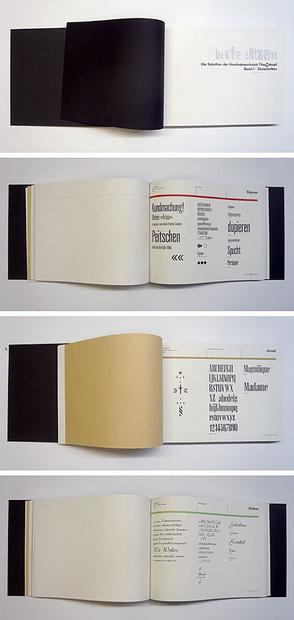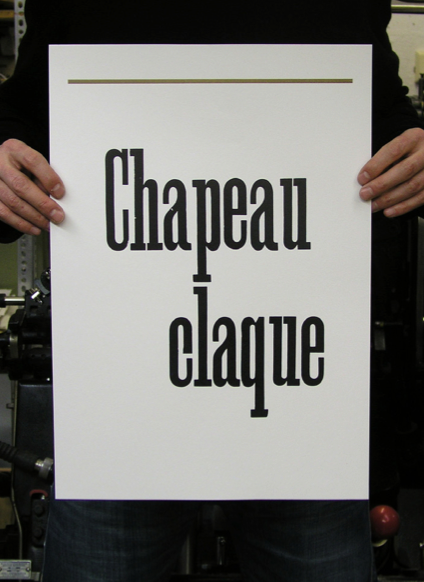
Unter dem Appell »Bitte setzen!« startete die Designschule München in Zusammenarbeit mit der Handsatzwerkstatt Fliegenkopf im Sommer 2008 ein gewagtes Unternehmen: Ein Schriftmusterbuch der rund 170 verschiedenen Schriften der Werkstatt sollte entstehen.
Was zunächst mit den Studierenden begann, wurde bald auf weitere Schriftliebhaber ausgedehnt. Viele entschlossen sich spontan, bei diesem außergewöhnlichen Projekt dabei zu sein und erweiterten den Kreis der Mitarbeiter weit über die Designschule hinaus. Annähernd 100 »Nachwuchssetzer« hatten am Ende mitgewirkt.
In den 20 Jahren seit Gründung der Handsatzwerkstatt Fliegenkopf hatten sich viele Schriften angesammelt, auch unbekannte und namenlose. Die betreuenden Lehrkräfte, Oliver Linke und Michael Wörgötter recherchierten in akribischen Nachforschungen die fehlenden Informationen zu den Schriften.
Für den Satz wurden Texte aus den Bereichen Dadaismus und Konkrete Poesie sowie alte und vergessene Wörter verwendet. So präsentiert das Schriftmusterbuch nicht nur die Schriften der Werkstatt mit Informationen zu ihrer Herkunft, sondern ist ganz nebenbei auch noch zu einer vergnüglichen Lektüre geworden, die Literatur und Wortschatz der Bleisatz-Ära dokumentiert.
Das komplette Werk setzt sich aus folgenden Teilen zusammen:
- Band I (122 Blatt, 35 x 25 cm) enthält die Bleischriften (89 verschiedene Schriften, z.T. komplette Schriftfamilien).
- Band II (ca. 100 Blatt, 35 x 25 cm) enthält die Plakatschriften (81 verschiedene Schriften), wobei Schriften in Graden über 12 Cicero zusätzlich auf 62 großen Schriftblättern (35 x 50 cm) abgedruckt wurden und in einer zusätzlichen Kassette erhältlich sind.
Schriften:
- Antiqua: Amati, Azuree/Allright, Bembo, Bodoni, Candida, Delphin, Deutsch-Römisch, Fette Lo, Forum, Garamond Freie Initialen, Garamond, Gravira, Kreß-Versalien, Kumlien, Liberta-Antiqua, Noblesse, Normande, Palatino, Post-Antiqua, Post-Versal, Promotor, Recta kursiv, Schadow-Antiqua, Schmale Egyptienne, Schmale Renaissance, Schreibmaschinenschrift, Thannhäuser-Schrift halbfett, Verzierte Italienne, Weiß-Antiqua, Weiß-Lapidar, Weltantiqua
- Grotesk: Akzidenz-Grotesk, Aurora, Block, Edel-Grotesk, Folio, Friedrich-Bauer-Grotesk, Futura, Gill, Graphique, Helvetica, Lichte fette Grotesk, Longina, Placard bold Condenses No.?2, Rhythmus, Roland-Grotesk, Schaefer-Versalien, Senta, Signum, Univers, Venus
- Schreibschriften: Bison, Butterlfly, Diskus, Forelle, Impuls, Isolde, Jaguar, Lithographia, Prägefest, Quick, Reporter, Salto, Signal, Virtuosa II
- Fraktur: Alte Schwabacher, Amts-Fraktur, Bernhard-Fraktur, Bismark-Fraktur, Deutschmeister, Ehmke-Schwabacher, Elite-Kanzlei, Fette Richard-Wagner-Fraktur, Fraktur Nr.?16, Gotenburg, Grobe Gotisch, Kanzlei, Luthersche Fraktur, National, Neue Schwabacher, Walbaum-Fraktur
- Fremde Schriften: Amtsantiqua halbfett cyrillic, Fundamental-Grotesk cyrillic, Russisch-Romanisch mager cyrillic, Russisch-Romanisch schmalhalbfett cyrillic, Griechisch: Verschiedene Schriften, Hebräisch: Verschiedene Schriften, Japanisch: Hiragana und Katagana, Chinesisch: Chinese Simplified
- Verschiedenes: Jugendstil-Schmuck, Reihenschmuck, Linien, Typo-Symbole, Klischees zu verschiedenen Anlässen, Vignetten und anderes